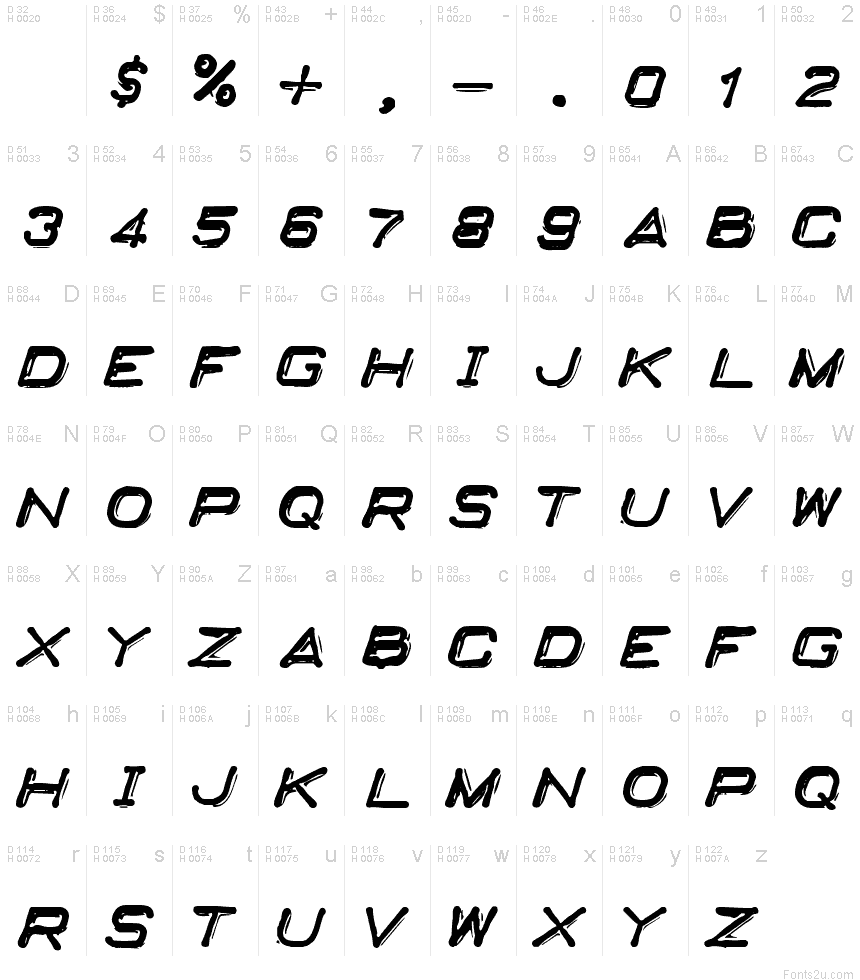
Embossing Tape 2 (BRK) od ÆNIGMA FONTS to darmowy, ozdobny krój pisma o erozyjnym charakterze, wyglądający jakby został wybity na ziarnistej taśmie etykietującej i przeciągnięty po chropowatej powierzchni. Masywne, pochylone litery z wyszczerbionymi krawędziami i nieregularnymi odstępami nadają każdemu słowu dotykową, zniszczoną energię, która przykuwa uwagę. Stosuj go w dużym rozmiarze i pogrubieniu, aby zachować wyrazistość i czytelność postarzanych krzywizn oraz zadrapanych wnętrz liter w swoich projektach.
Dzięki Embossing Tape 2 (BRK) nadasz surowy, industrialny charakter plakatom, okładkom albumów, zinom, tytułom horrorów, grafikom streetwearowym, wlepkom i banerom w mediach społecznościowych. Szerokie, pochyłe formy tworzą szybki, dynamiczny rytm, który sprawia wrażenie ręcznej roboty, ale pozostaje pod kontrolą – idealne rozwiązanie do nagłówków, które potrzebują wyrazu, ale muszą pozostać czytelne. Ten darmowy font świetnie komponuje się z czystym, neutralnym krojem bezszeryfowym w tekście głównym, pozwalając jego surowej teksturze wyjść na pierwszy plan.